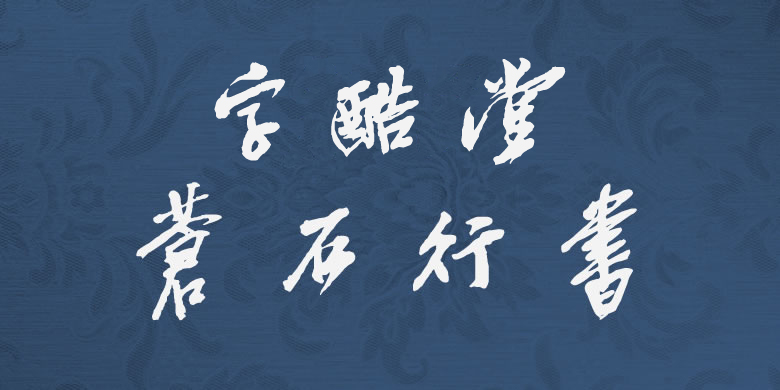
字酷堂苍石行书
品牌:方正字库字酷堂设计师:过中运发行时间:2017字库编码:繁U(GB12345-90-U)分类:常规书写·毛笔字体属性:精品字
吴昌硕(1844—1927)初名俊,又名俊卿,字昌硕,又署仓石、苍石,多别号,常见者有仓硕、老苍、老缶、苦铁、大聋、缶道人、石尊者等。晚清民国时期著名国画家、书法家、篆刻家,“后海派”代表,杭州西泠印社首任社长,与任伯年、蒲华、虚谷合称为“清末海派四大家”。篆刻家,与任伯年、赵之谦、虚谷齐名为“清末海派四大家”。其书法用笔多以中锋篆隶笔法,富有金石气息,结体开张爽健,有雄强老辣的艺术感染力。吴昌硕留下了大量书作,画作也多有长款,搜集遴选并调整补充,做成了这款字库。